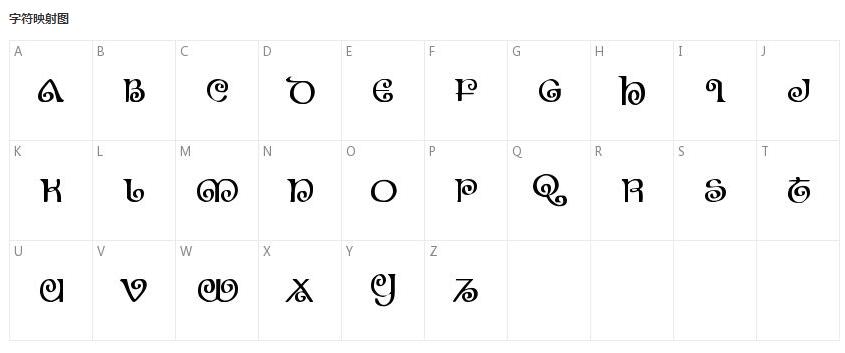
The-Shire.ttf类型,T字母英文是一款非常漂亮的艺术字体,The-Shire.ttf类型,T字母英文字体广泛用于各种书刊、画册的设计印刷中,The-Shire.ttf类型,T字母英文字体具有强烈的视觉冲击力,报纸和杂志和书籍中常用
The-Shire.ttf类型,T字母英文是一款非常漂亮的艺术字体,The-Shire.ttf类型,T字母英文字体广泛用于各种书刊、画册的设计印刷中,The-Shire.ttf类型,T字母英文字体具有强烈的视觉冲击力,报纸和杂志和书籍中常用字体, 海报、个性促进品牌标志设计、字体设计、等环境。 The-Shire.ttf类型,T字母英文字体是一款用于标题设计方面的字体,由字体下载站提供免费下载,字体下载大全提供最全最新的中、英文字体素材。